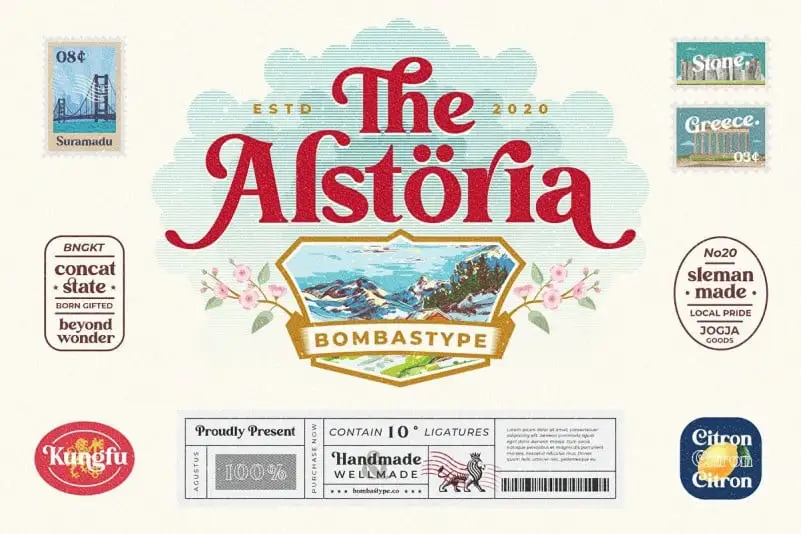
A Alstoria Serif Font é uma alegria para os olhos com sua paleta moderna e vintage. Ela traz novas alternativas e ligaturas, tornando-a ainda mais vibrante e versátil. É um tipo bold display serif perfeito para projetos de marca, embalagens, impressão, cabeçalhos e muito mais. Possui 320+ glyphs e 10 ligaturas incorporadas, além das muitas alternativas de swash que oferecem liberdade criativa. A fonte é uma jóia perfeita para estilos vintage e moderno, como você pode ver em nossas imagens de preview. Ideal tanto para profissionais de design quanto para iniciantes, ela traz um toque singular a qualquer projeto.